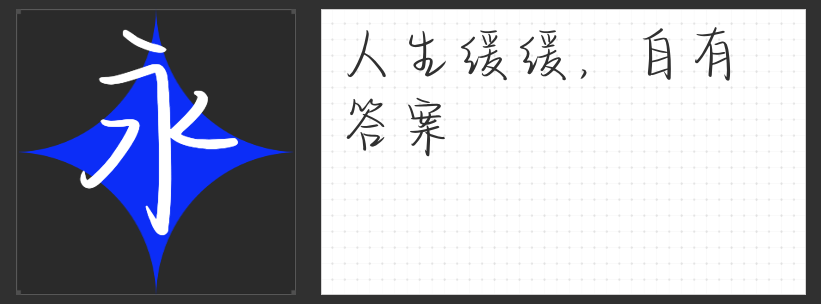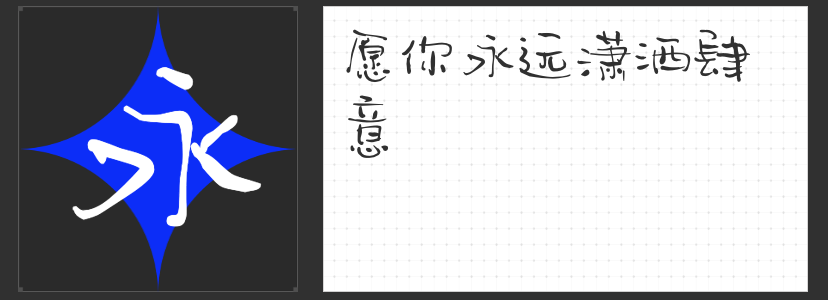
字游同人界:精选字体,助力手书视频创意飞扬
在创意无限的同人手书视频世界里,字体不仅是文字的载体,更是情感的传递者,能够瞬间引领观众进入不同的视觉与情感领域。今天,就让我们一同揭开四款适合同人手书视频设计的字体面纱,它们各自拥有着独特的魅力,能够为你的作品增添无限风采。
1. 喵字文案体
专为可爱风格定制,这款字体圆润饱满,线条流畅,仿佛每一笔都透露出慵懒与温柔。它最适合用于打造萌系、治愈系的同人手书视频,无论是角色间的温馨互动,还是日常的甜蜜瞬间,喵字文案体都能完美诠释那份纯真与美好。
2. 高手字斋哥特体Pro
踏入个人向、哥特风同人手书视频的神秘领域,高手字斋哥特体Pro无疑是最佳选择。其独特的尖锐边角与深邃笔触,营造出一种神秘而高贵的氛围。无论是描绘黑暗世界的冒险故事,还是展现角色内心的挣扎与挣扎后的蜕变,这款字体都能精准传达那份独特的风格魅力。
3. 也字工厂雨眠手迹
清新、恋爱的同人手书视频,怎能少了也字工厂雨眠手迹的陪伴?这款字体如同细雨中的一抹温柔,笔画轻盈而不失力度,字里行间透露出淡淡的忧伤与甜蜜。它适合用来书写那些关于青春、初恋与成长的故事,让观众在字里行间感受到那份清新脱俗的恋爱气息。
4. 小豆岛默陌枝桠简
这款字体融合了古风的典雅与现代设计的简约,既不失传统韵味,又带有几分轻松幽默。它适用于古风题材的同人手书视频,无论是讲述一段跨越时空的爱恋,还是演绎一场啼笑皆非的搞笑剧情,都能让观众在欢笑中感受到古风的魅力。
选择适合的字体,就如同为同人手书视频穿上了一件得体的外衣,让作品更加生动、更加引人入胜。希望这四款字体能成为你创作路上的得力助手,让你的同人手书视频更加精彩纷呈。